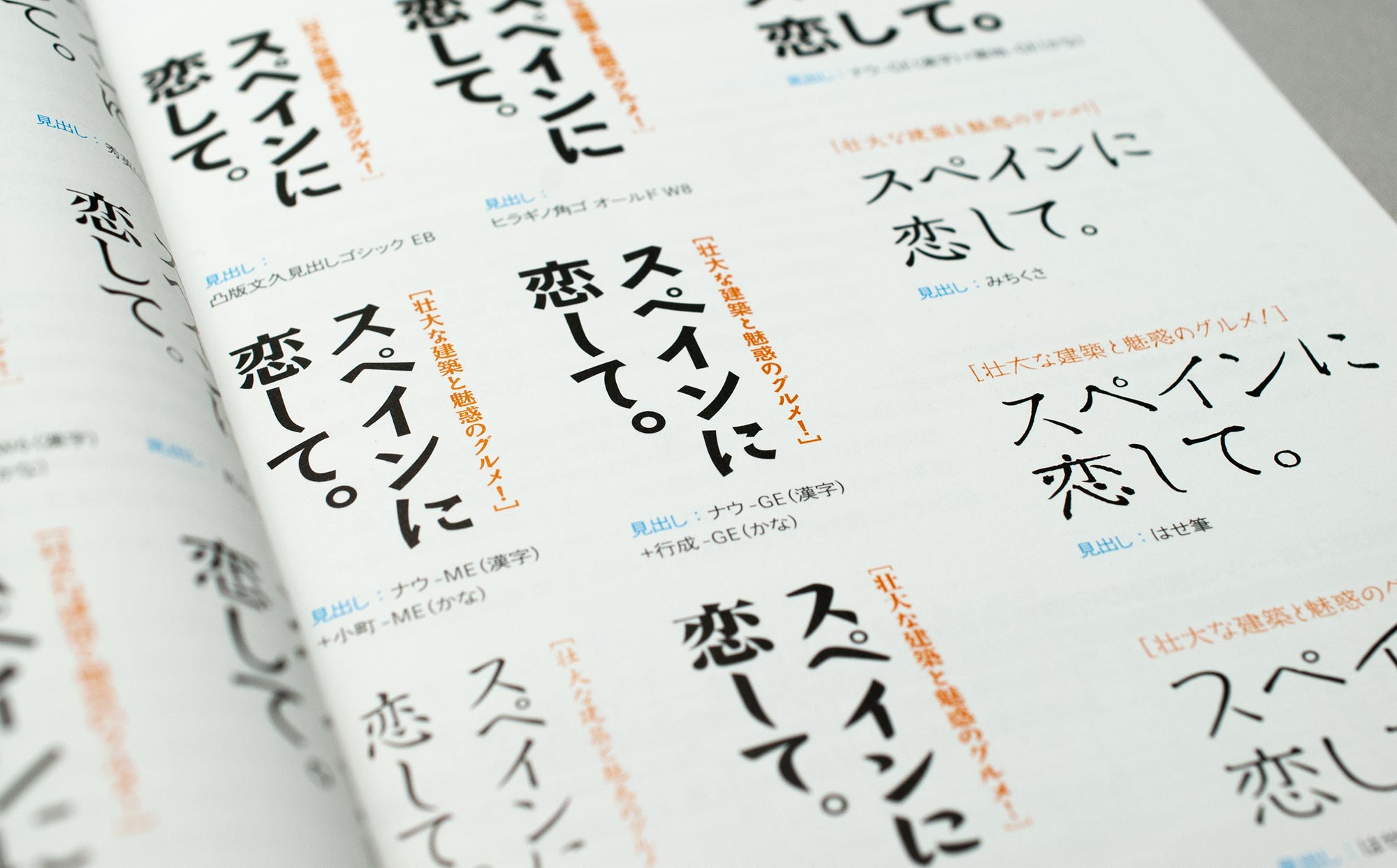
Schrift und Image
Nicht ohne Grund gibt es so viele Schriftarten in unserer Gesellschaft. Jede Schriftart vermittelt einen anderen Eindruck. Wer sich auch typografisch sein eigenes Image geben will, braucht die passende Schriftart. Das gilt auch für Japanisch.
verschiedene japanische Schriftarten
Schrift und Image in Europa
Corporate Design ist ein wichtiger Teil der Corporate Identity und bestimmt das Erscheinungsbild eines Unternehmens. Die entscheidende Rolle spielt dabei – die Schrift. Sie wird in allen Kommunikationsmitteln konsequent verwendet und leistet einen genauso großen Beitrag für den Wiedererkennungseffekt des Unternehmens wie das Unternehmenslogo. Sie haben bestimmt auch schon erlebt, dass Sie bei einer Werbung gleich an der Schriftart unterbewusst erkennen, für welches Unternehmen geworben wird.
Anders als Kanji, wie die chinesischen Schriftzeichen in Japan genannt werden, haben die lateinischen Buchstaben äußerst klare und einfache Formen. Das bedeutet für Typedesigner große Flexibilität und Freiheit. Außerdem enthält das lateinische Alphabet nur wenige Buchstaben. Europa hat deshalb bereits eine lange Geschichte des Typedesigns und heute ist die Zahl der Schriftarten so groß, dass niemand mehr ihre genaue Zahl weiß. In Europa hat es quasi immer die optimale Voraussetzung für die Entstehung und Umsetzung des Gedankens gegeben, eine Schriftart ins Corporate Design zu integrieren.
Im Zeitalter der digitalisierten Schriften wird nicht nur einfach eine beliebige Schriftart ausgesucht und verwendet, die auf dem Markt verfügbar ist, sondern zunehmend wird sie auch modifiziert, damit die Individualität noch steigt. Heute ist es sogar keine Seltenheit mehr, dass ein Unternehmen Typedesigner damit beauftragt, eine eigene Schrift zur exklusiven Nutzung anzufertigen (siehe: Hausschriften-Liste bei Typografie.info).
Schriftart und Wirkung
In den folgenden beiden Abbildungen sehen Sie, wie langweilig unser Alltag mit einer einzigen Schriftart aussehen kann, und eben das Gegenteil, wie bunt und verständlich er auch sein kann, wenn eine passende Schriftart, die eine inhaltsbezogene Atmosphäre schafft, für jeden Begriff gekonnt ausgewählt ist.
Schriftarten Helvetica und MS Gothic
Japanische Schriftarten
Imageübertragung ins Japanische
Für die Herstellung des Originals Ihrer Kommunikationsmittel scheuen Sie keine Kosten und Mühen, investieren viel Zeit. Nicht wenige arbeiten mit einer Werbeagentur zusammen. Die Schriftart, -größe, -farbe und das Layout werden nicht nach Belieben, sondern von erfahrenen Profis gezielt herausgearbeitet. Das »Image« wird sichtbar. Die englische oder französische Sprachversion für den Export sieht genauso hübsch aus wie das Original, aber … wie sieht die japanische Fassung aus? Ist sie noch vergleichbar mit dem Original?
Der direkte Vergleich zwischen der deutschen und der japanischen Sprachversion eines Schriftstücks scheint wegen des grundverschiedenen Charakters der Schriften auf den ersten Blick nicht möglich. Aber Japaner und Deutsche sind doch gleichermaßen Menschen. Was Titel, Überschriften, Zwischenüberschriften, Fließtext und sonstige andere typografische Elemente angeht, haben beide die gleiche Art der Wahrnehmung. Unabhängig von der Sprache haben wir ein ähnliches Empfinden für die gesetzten Texte.
Das heißt, wenn man mit japanischsprachigen Kommunikationsmitteln die gleiche Wirkung bei Japanern erzielen will, wie mit deutschsprachigen bei Deutschen, müssten die wesentlichen typografischen Strukturen auch bei der Übertragung ins Japanische streng eingehalten werden. Unter diesen Gesichtspunkten sollte man prüfen, ob beide Versionen den gestellten Ansprüchen auch gerecht werden. Wie sind die Schriftgröße, Schriftstärke, Zeilenabstände und die Aufteilung der Weißräume?
Kuriose Drucksachen aus Europa
Berufsbedingt habe ich bisher eine Menge kuriose japanische Drucksachen und Websites gesehen, die anscheinend in Europa angefertigt worden sind. Die meisten davon wurden von japanischunkundigen Europäern erstellt, der Rest stammte von Japanisch-Übersetzern, die zwar gut schreiben aber nicht richtig setzen können. Hierzulande werden Dinge einfach in Druck gegeben, die in Japan undenkbar wären. Aber Papier ist ja bekanntlich geduldig. Oft tun mir die Japaner leid, die die japanische Fassung wirklich brauchen. Einige amüsieren sich bestimmt über die Kuriositäten, aber das dürfte keiner der Herausgeber beabsichtigt haben.